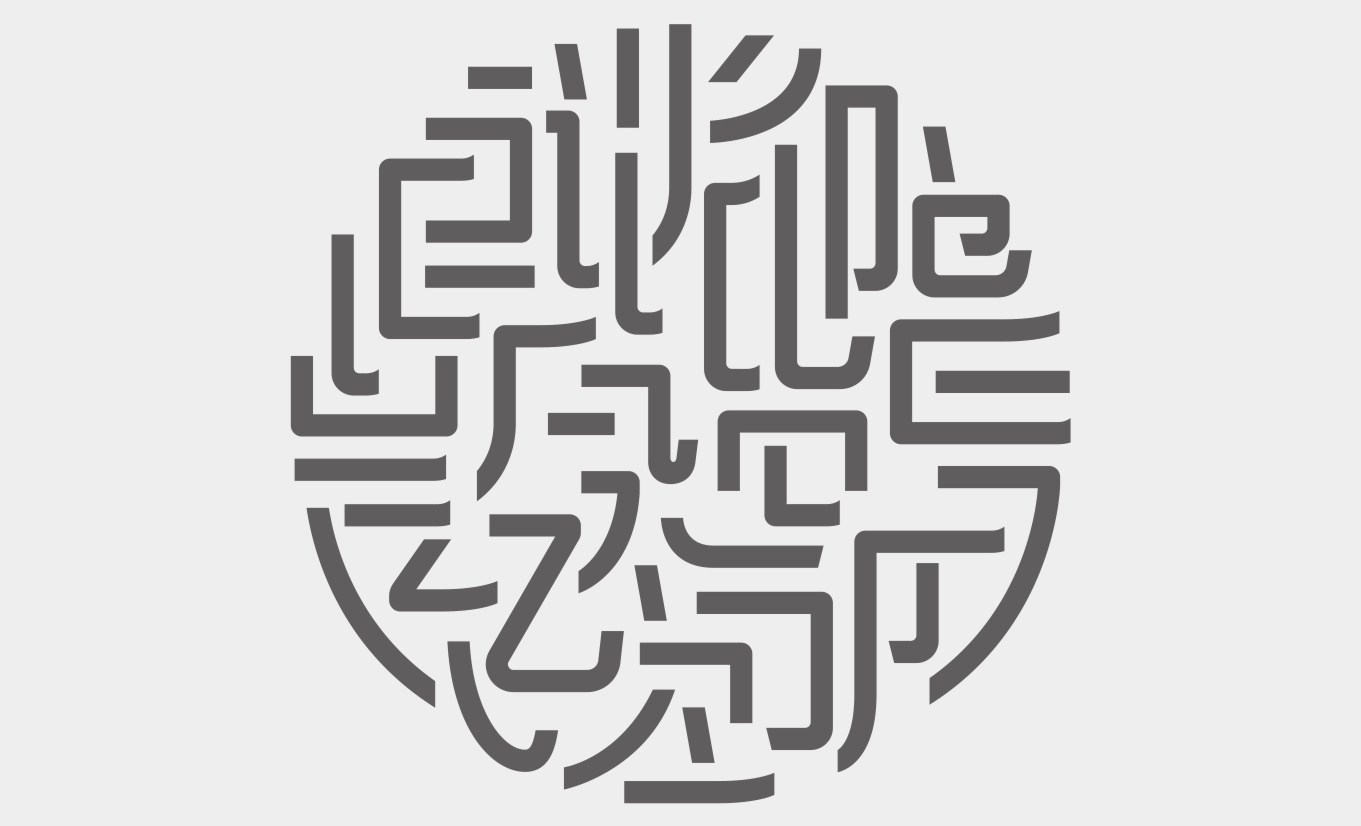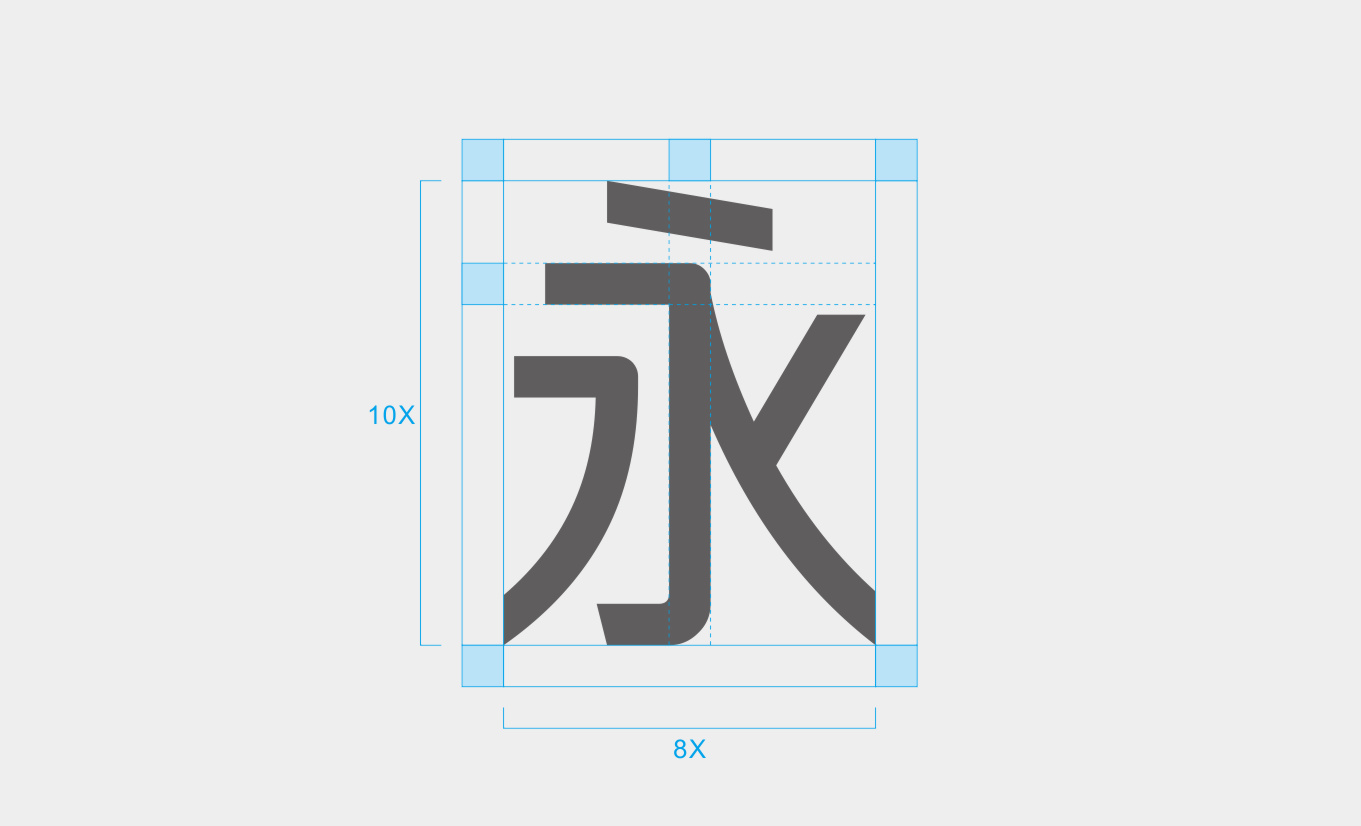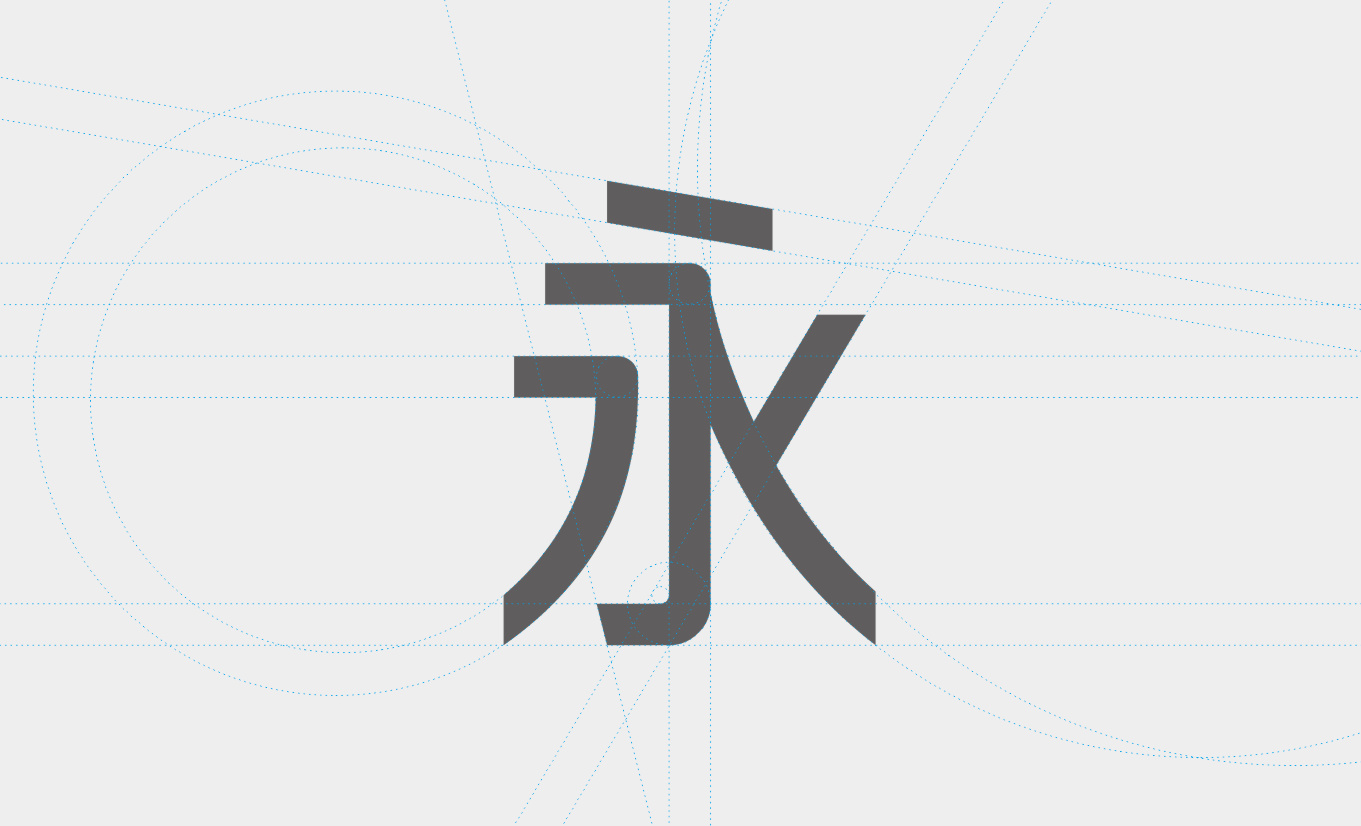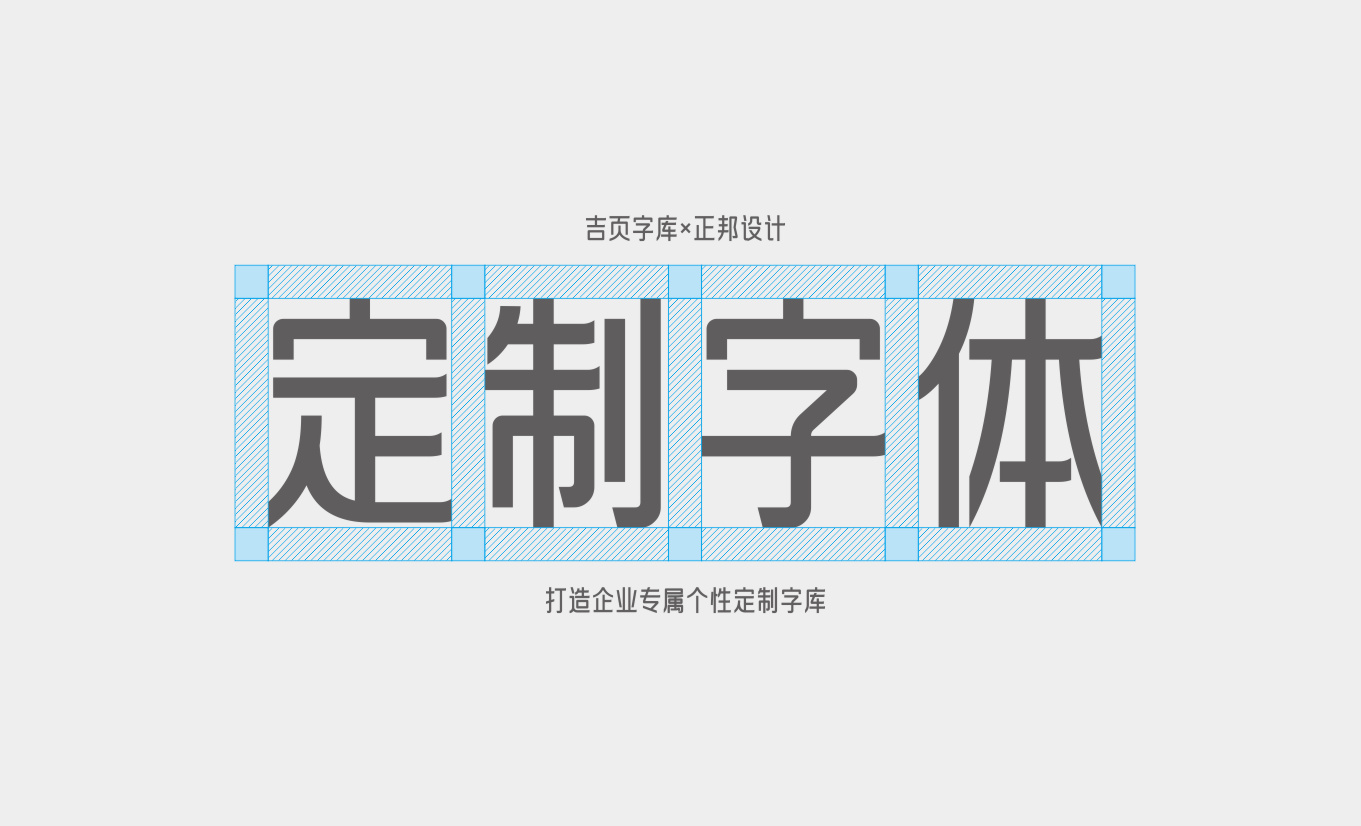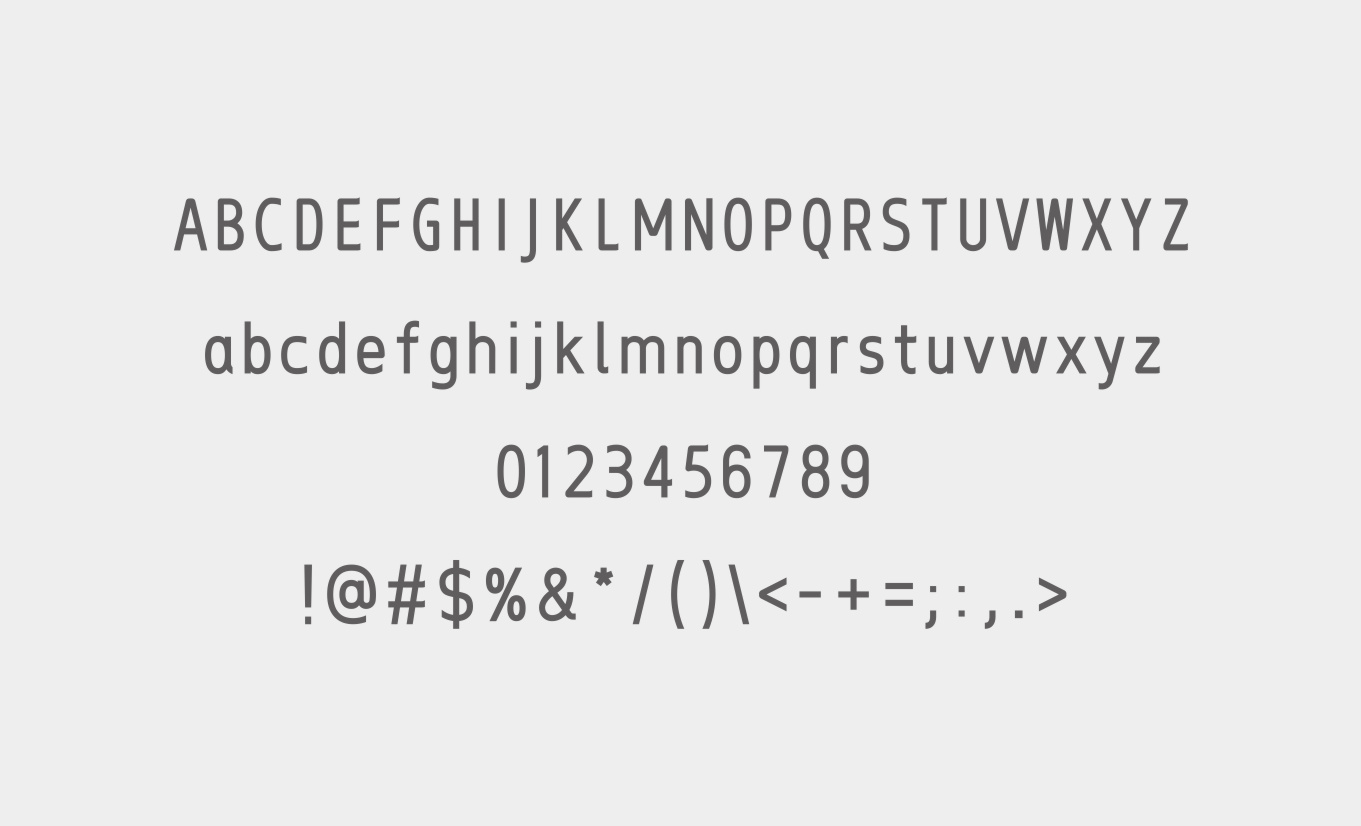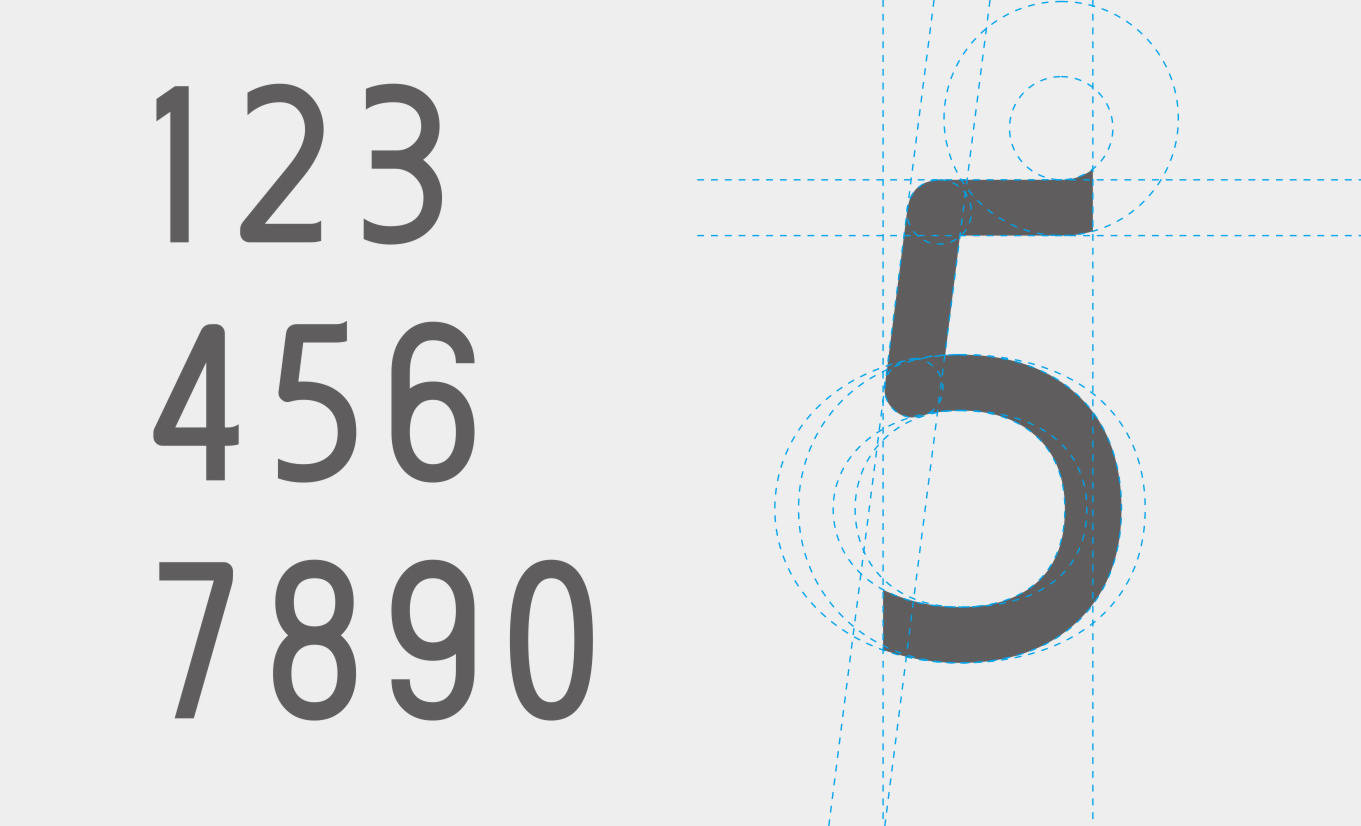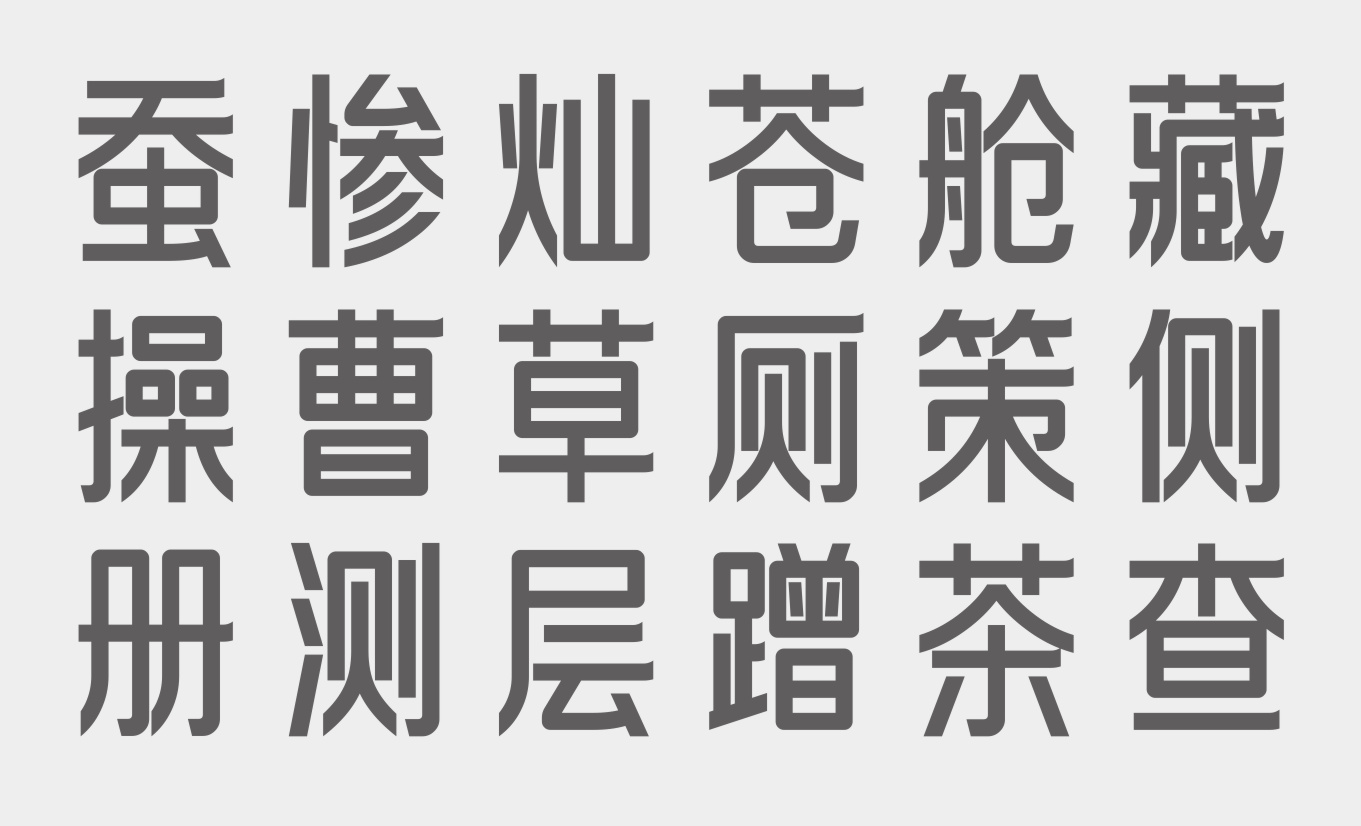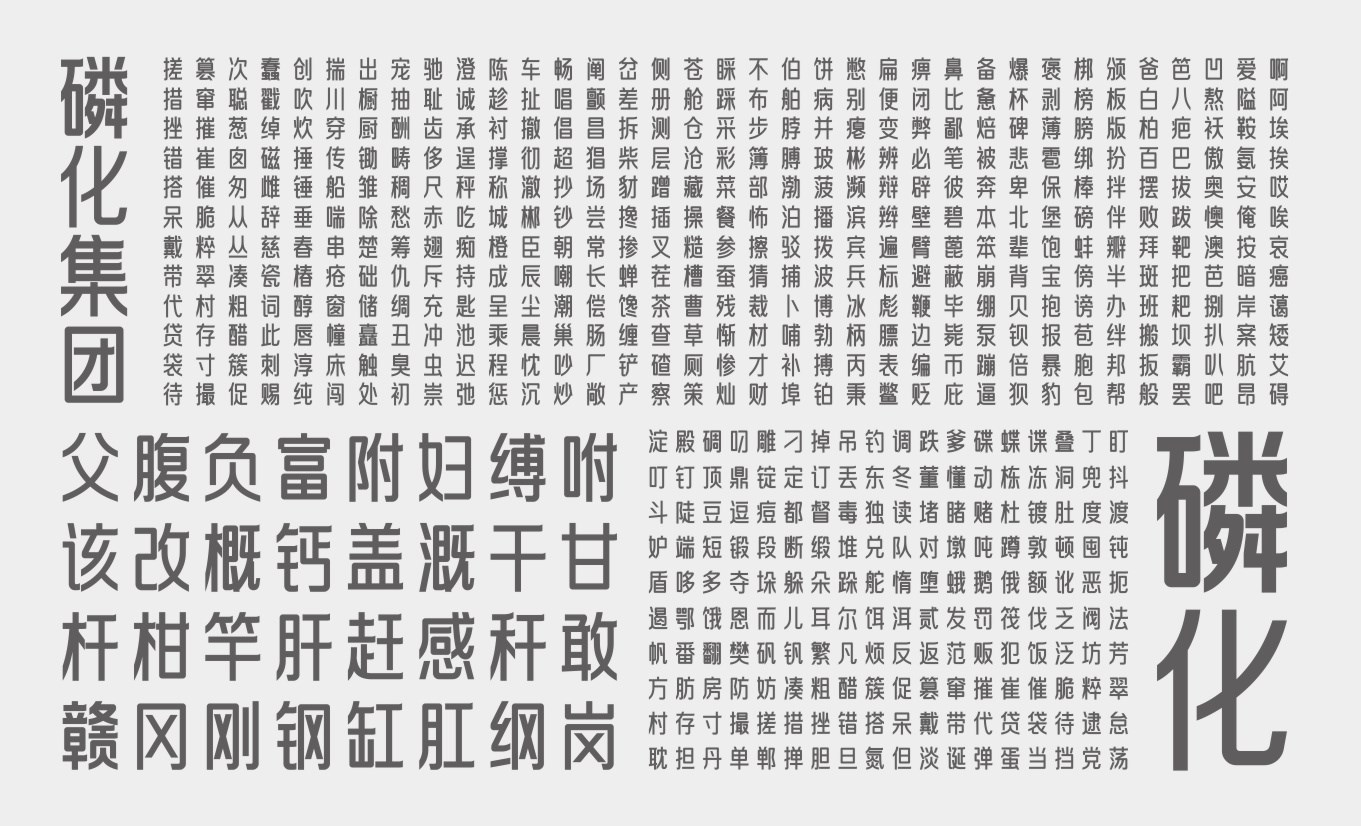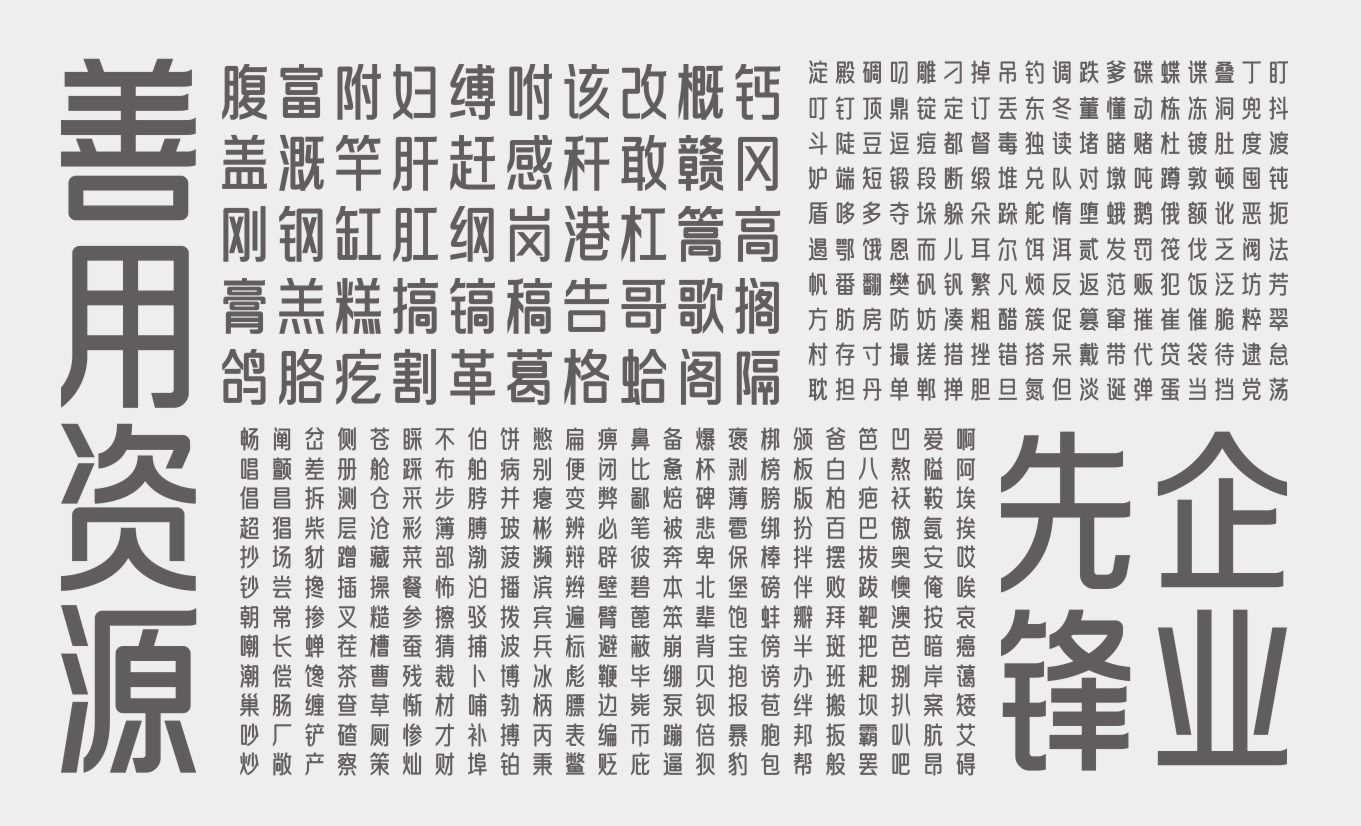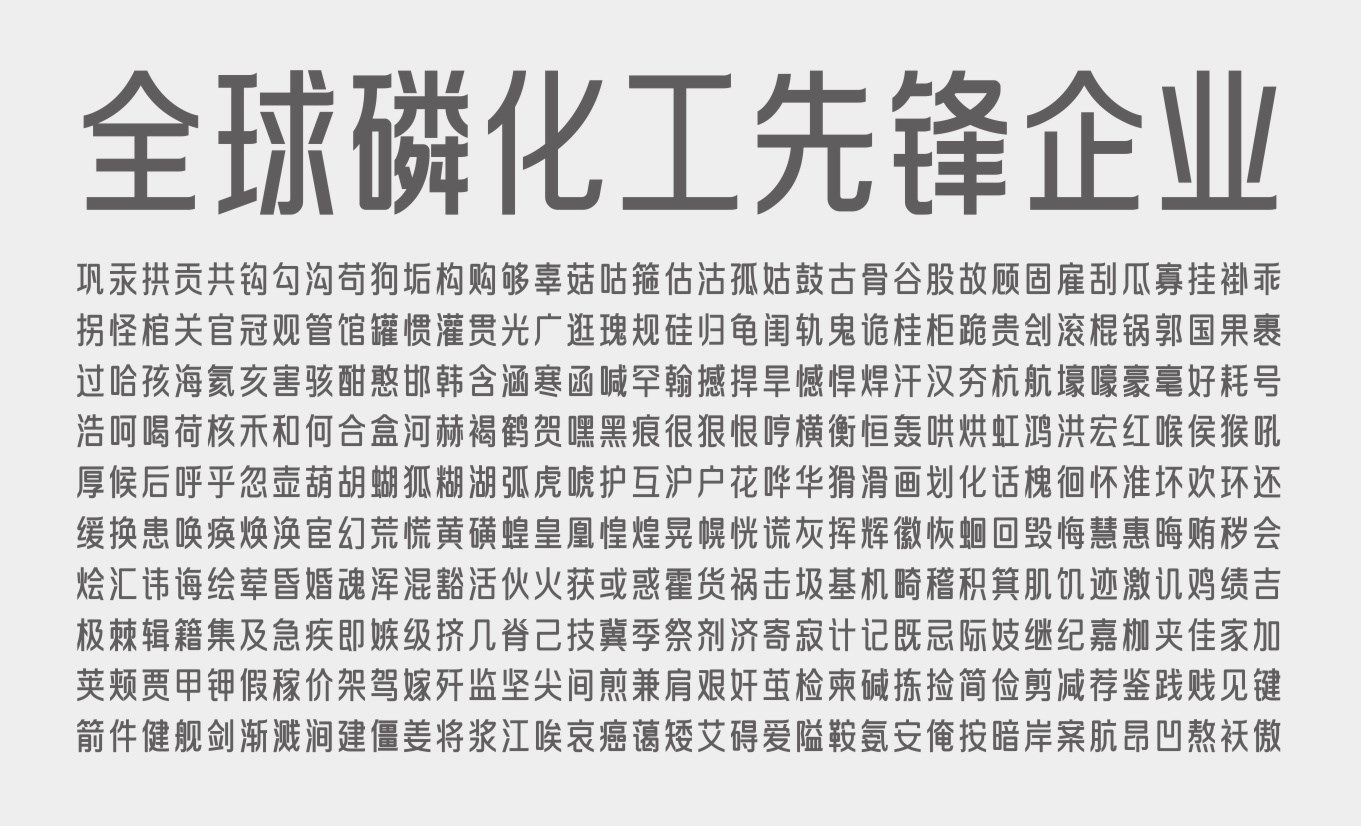
磷化黑体-定制字库
磷化黑体是北京正邦设计邀请吉页字库为其客户定制的一款字体。磷化黑体收入了汉字字符3600+、西文、数字以及常用的标点符号。
最初吉页字库为其提供了3套方案,最终客户选择了此款方案。
磷化黑体除了常用3500个汉字,又添加了客户行业中常用的一些汉字。其字体风格融入了衬线的装饰,字身修长,相比传统黑体,在稳重的基础上又增添了一些亲和感。
此图为磷化黑体的一些常用笔画。
整体采用8:10的比例,笔画除了衬线,均运用了视觉等线宽。
字体在设计开发中均以专业严谨的态度,打造精品。
西文、数字、符号